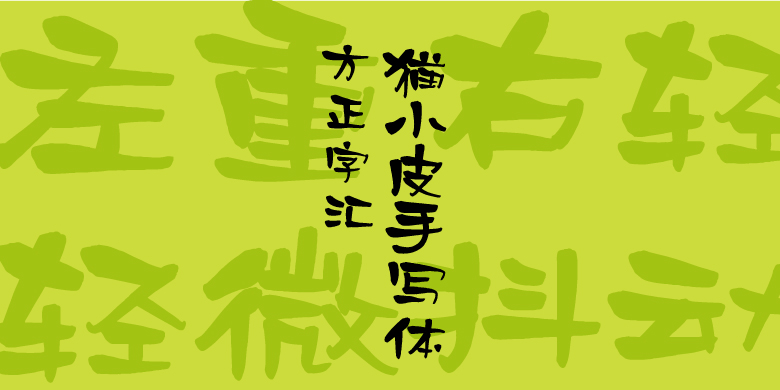
方正字汇-猫小皮手写体
方正字汇-猫小皮手写体,这款字体结构工整、笔画清晰,兼顾美观与易读性,适用于标题、正文、海报、包装、LOGO 等多种场景。字形优雅稳定,风格百搭耐看,适配日常排版与创意设计,让文字呈现更舒适、更具质感。方正字汇-猫小皮手写体一笔一画,皆是细节,以均衡的比例、流畅的线条打造舒适视觉体验,字形端正大气,风格简约现代。无论是商业设计、品牌宣传还是日常排版,都能轻松驾驭,让文字更有格调与力量。方正字汇-猫小皮手写体字体下载。
字体品牌: 方正字汇 设计师:曾宸 字体分类:常规书写·毛笔 字体属性:精品字 字符集:大陆简体(GB2312-80)、简繁扩展(GBK) 发布时间: 2025